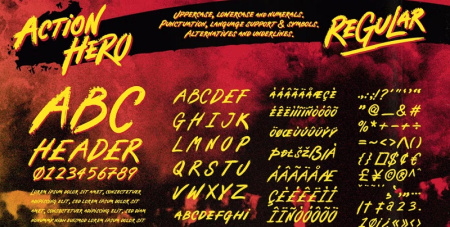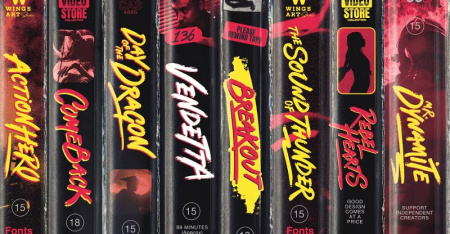
فونت انگلیسی پوستر فیلم Action Hero
فونت انگلیسی پوستر فیلم
فونت انگلیسی پوستر فیلم Action Hero از جی اف ایکس دانلود. این یک فونت زیبا با طراحی دست نویس است که از پوسترهای فیلم های اکشن دهه 1980 و 90 الهام گرفته شده است. شامل مجموعه کاملی از حروف بزرگ و کوچک، همراه با اعداد، علائم نگارشی، پشتیبانی از زبان های مختلف است. این فونت انگلیسی مخصوص طراحی پوستر و تبلیعات مناسب برای پوسترها، عناوین فیلم ها، بسته بندی محصول، پخش و تبلیغات می باشد.
✅ نام فونت انگلیسی: Action Hero
✅ شامل حروف بزرگ و کوچک، همراه با اعداد، علائم نگارشی
✅ پشتیبانی از زبان های مختلف